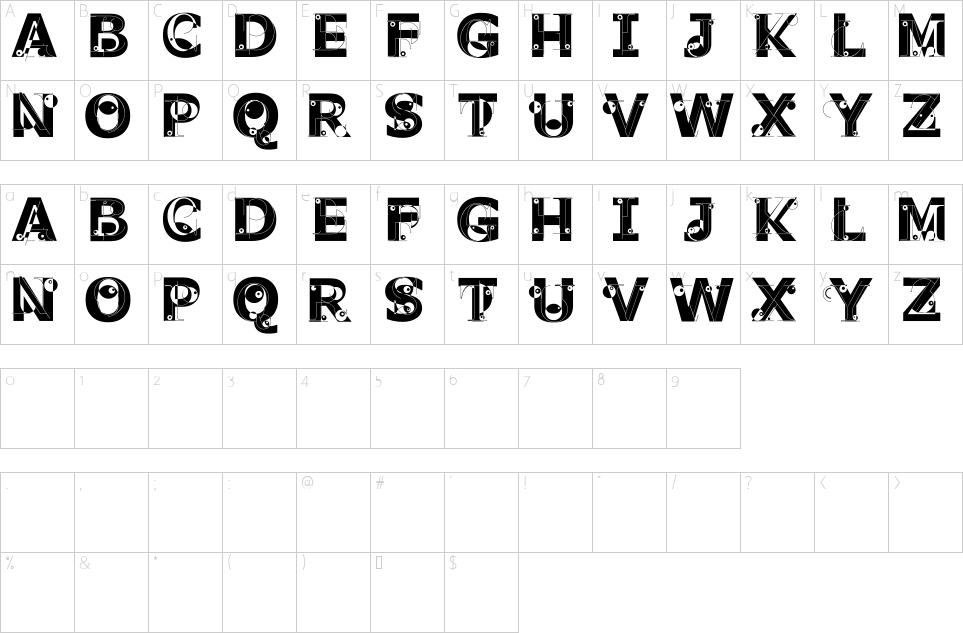
A Pablo Sans Caps é uma nova adição ao catálogo das fontes gratuitas que oferecemos aqui na nossa plataforma. Desenvolvida pelo criador Manfred Kleinw, esta elegante fonte caps de linhas grossas se destaca como um complemento perfeito para qualquer projeto digital ou impressão. Se você procura uma fonte com estilo moderno e forte, que combina suavemente com tipografias serifadas mais tradicionais, a Pablo Sans Caps pode ser o alvo da sua pesquisa. Confortável de ler e versátil em várias tamanhos, a Pablo Sans Caps será um elemento de destaque em sites, aplicativos móveis ou impressões digitais. Ela mantém sua beleza enquanto se adapta perfeitamente para diversos usos, seja em textos mais formais ou mais informais. A fonte é especialmente adequada para mídias sociais e design gráfico, oferecendo um toque atraente sem exagerar. Além disso, como uma fonte grátis que se destaca por sua alta qualidade e simplicidade no uso, a Pablo Sans Caps é perfeita tanto para designers iniciantes quanto para profissionais experientes. Seja você criando sites amigáveis ao usuário ou desenvolvendo layouts digitais, adicionar essa fonte à sua lista de favoritos pode revitalizar seu trabalho de design e torná-lo ainda mais atrativo aos olhos do público.